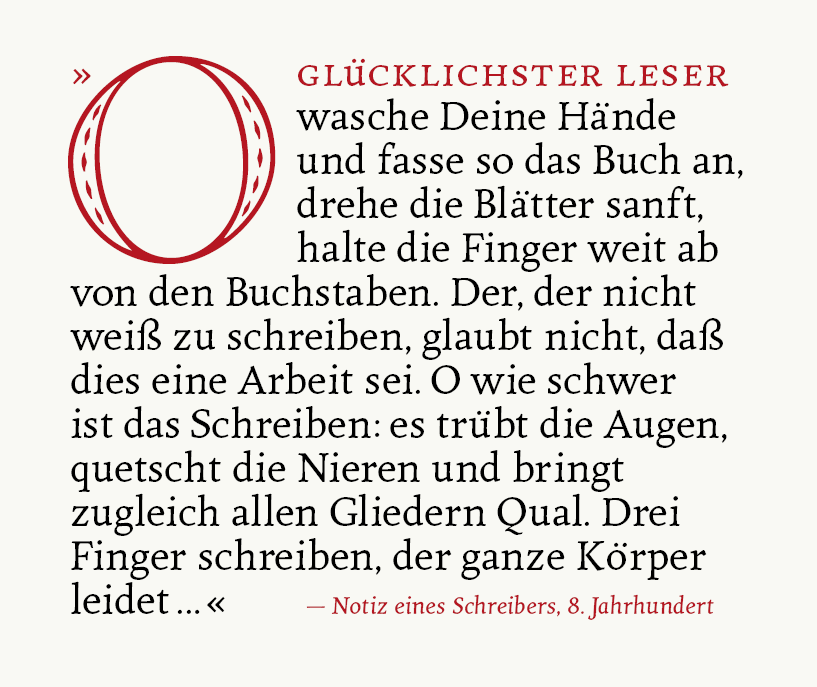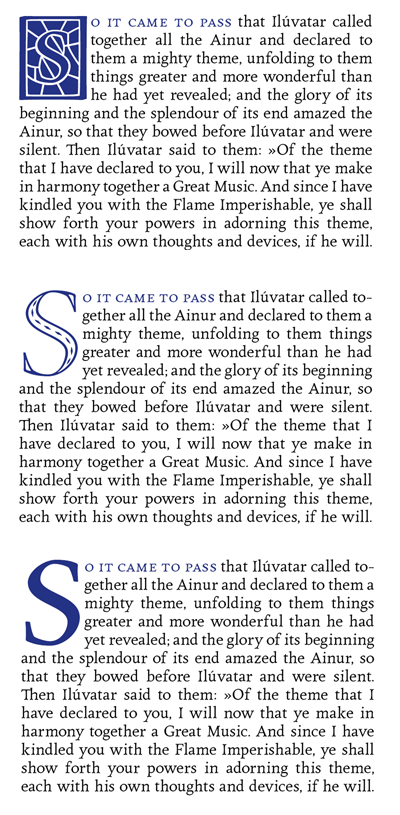
Gute Initialen?
Hier mal ein paar schnelle Screenshots aus einem alten Schriftmuster-Testdokument (ohne weitere Bearbeitung):
Diverse Schmuck-Versuche:
Die Problematik von Anführungszeichen und Einzelbuchstaben.
Allerdings sind beide Probleme nicht wirklich gelöst, die Form des "O" kommt sowohl dem Anführungszeichen als auch der Trennung zum Folgewort "entgegen":
Ich persönlich finde ja, daß bei Anführungszeichen Forssman und de Jong recht haben (Detailtypografie): die initiale Anführung wird einfach weggelassen. Das Initial steht in jedem Fall für einen komplett neuen Abschnitt. Sobald man dann beim lesen auf die schließende Anführung trifft ist auch normalerweise unmißverständlich klar, daß es sich um ein Zitat handelt. Die Anführung ist damit nicht zwingend notwendig. Im Prinzip funktioniert das gleiche Argument ja auch für die spanischen Satzzeichen.
Wenn das allerdings mehr als einmal vorkommt stellt sich natürlich die Frage ob Initialen überhaupt im Werk angebracht sind.
Aber das ist jetzt nur mein persönliches Gefühl.
Edith meint: Sebastian, da hast Du natürlich ein übles Beispiel gewählt. Wenn ein Zitat so derart lang ist, dann wird es durchaus problematisch. Wobei mir die drangeklebte Anführung beim schnellen Lesen auch schlicht entgangen ist.
Mit Druck habe ich diesbezüglich keine Erfahrung, aber bzgl. der Anwendung im Web kann ich einen kleinen Erfahrungswert besteuern. Vor längerer Zeit habe ich in eine Seite mit kundenerstellten Kolumnen zur Auflockerung ungefragt einfach mal die Initialen des 1. Absatzes wie folgt heraus gestellt. Heute würde ich das bestimmt anders machen, aber damals habe ich weder an Kapitälchen für die erste Zeile noch daran gedacht, zwischen ein- und mehrbuchstabigen Wörtern zu unterscheiden. Es hat sich trotzdem niemand über Zweideutigkeiten oder Leseschwierigkeiten beschwert – und das waren Leute, die wirklich über jeden Fliegenschiss ausgiebigst gemeckert haben. So sah’s aus:
Ein Live-Beispiel – diesmal mit Kapitälchen in der ersten Zeile – gibt’s hier zu sehen. Es zeigt auch, wie Anführungszeichen gehandhabt werden. Das ganze lässt sich natürlich noch erheblich ausbauen, z.B. mit einer Webfont-Familie, die echte Kapitälchen bietet.
Bei mir so:
Ich find das nicht unbedingt gelungen.
Aus dem oberen link entspringt auch eher optisches Gulasch:
Like, so ...? :-?
Finde ich schick. Jetzt hätte ich fast mal Lust sowas zu setzen.
Ich glaub bei eben solchen Probleme muss man einfach kreativ werden und eine eigene Lösung suchen.
Genau, das ist das Wichtigste :)
Die einzigen Regeln die wirklich wichtig sind:
- Wird die Lösung vom potentiellen Leser verstanden?
- Kann die Lösung nicht gegensätzlich falsch verstanden werden?
- Ist die Lösung ästhetisch?
(- lässt sie sich mit adäquatem Aufwand realisieren?)
Ein Beispiel mit Webfont und echten Kapitälchen Was meinen die Profis? Wäre das so einsetzbar? Wie ginge es besser?
Also, so wie es bei Dir aussieht ist es ziemlich cool, beeindruckend, was man mit html und css (oder ist das js??) anstellen kann :)
Frage ist, ob die oberste Zeile sich automatisch ändert, wenn man zB zoomt; dadurch dass nicht umgebrochen wird, kann man ja durchaus die ganze erste Zeile in Kapitälchen setzen, statt nur die ersten x Wörter, aber wie sieht das aus, wenn ich zoome und ein Wort in die nächste Zeile rutscht ...? :) Bei mir (Win7, Opera) sieht es momentan leider so aus wie im Anhang ... :/
Finde ich schick. Jetzt hätte ich fast mal Lust sowas zu setzen.
Danke ;) Ich find auch, gerade mit nem Satzzeichen hat das was, es wirkt noch verzierter, wenn etwas so deutlich aus dem Satzspiegel herausragt :)
Ich glaub bei eben solchen Probleme muss man einfach kreativ werden und eine eigene Lösung suchen.
Genau, das ist das Wichtigste :)
Die einzigen Regeln die wirklich wichtig sind:
- Wird die Lösung vom potentiellen Leser verstanden?
- Kann die Lösung nicht gegensätzlich falsch verstanden werden?
- Ist die Lösung ästhetisch?
(- lässt sie sich mit adäquatem Aufwand realisieren?)
Zustimmung in allen Punkten :))
Also, so wie es bei Dir aussieht ist es ziemlich cool, beeindruckend, was man mit html und css (oder ist das js??) anstellen kann :)
Frage ist, ob die oberste Zeile sich automatisch ändert, wenn man zB zoomt; dadurch dass nicht umgebrochen wird, kann man ja durchaus die ganze erste Zeile in Kapitälchen setzen, statt nur die ersten x Wörter, aber wie sieht das aus, wenn ich zoome und ein Wort in die nächste Zeile rutscht ...? :) Bei mir (Win7, Opera) sieht es momentan leider so aus wie im Anhang ... :/
:gimmifive: Dankeschön! Aber weißt Du was? Ich glaube, die wird’s nicht interessieren und dann haben sie die typografischen Leckerbissen auch nicht verdient … :-?
… noch einen Halbsatz ergänzt.
:schmunzel: Langsam beginne ich zu verstehen, warum Tschichold in seinen späteren Jahren so einen etwas verbitterten Eindruck gemacht hat ... ;-)